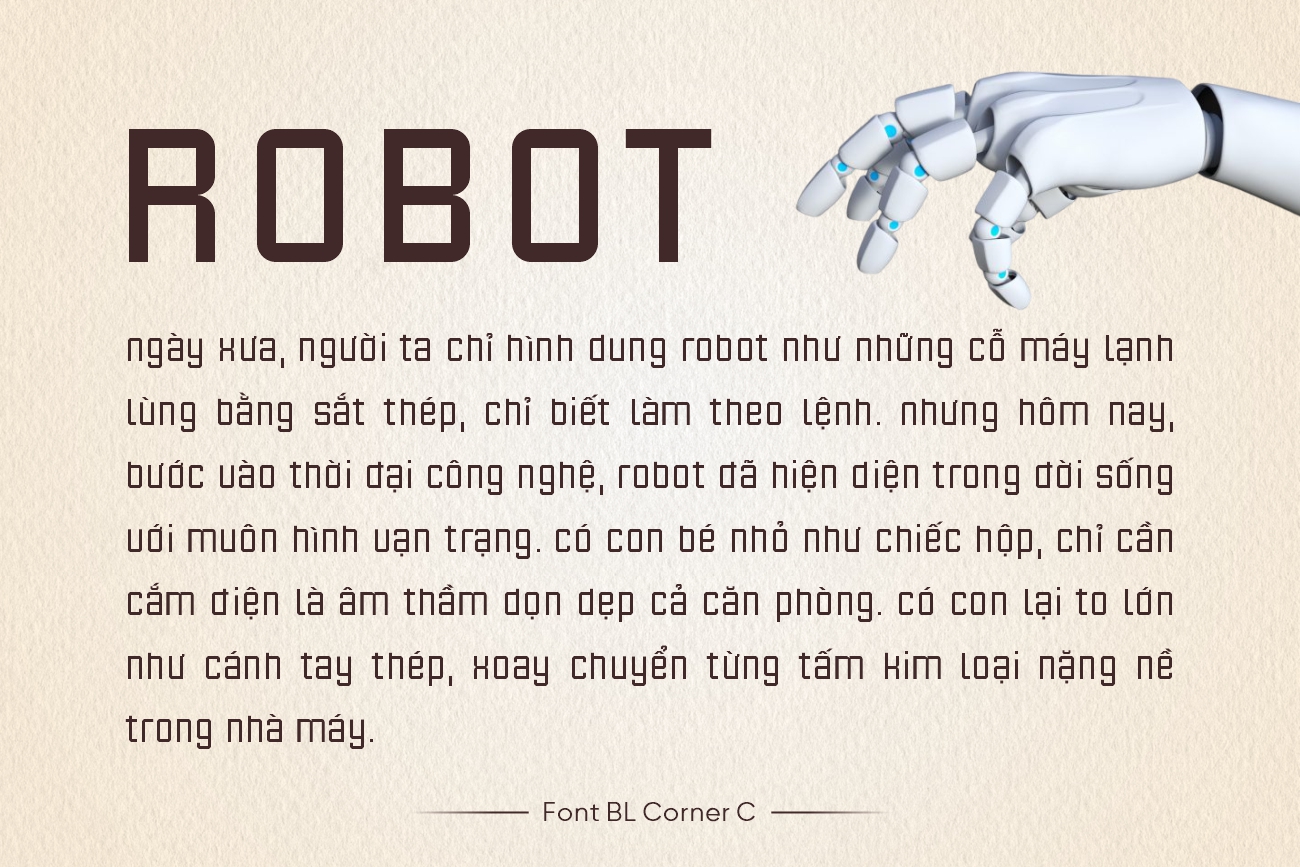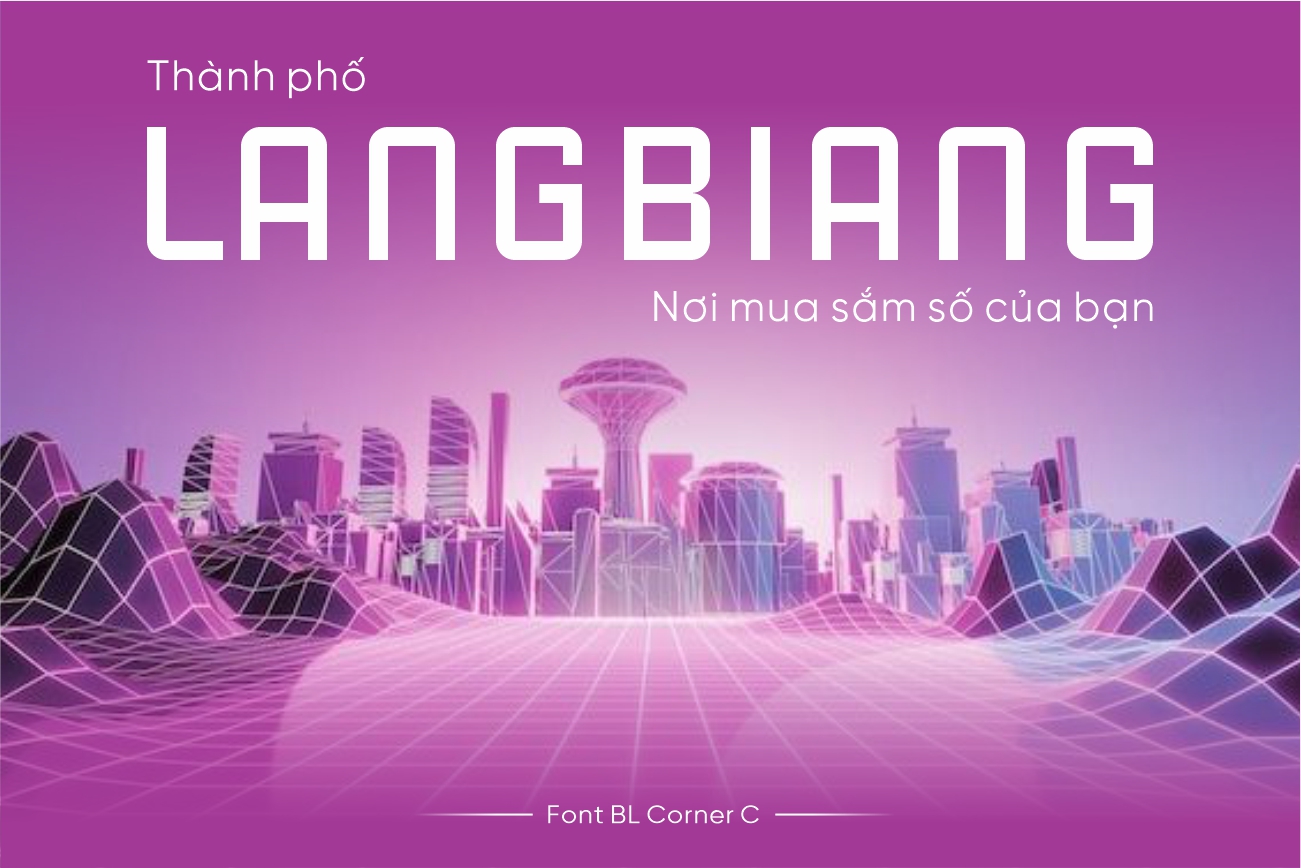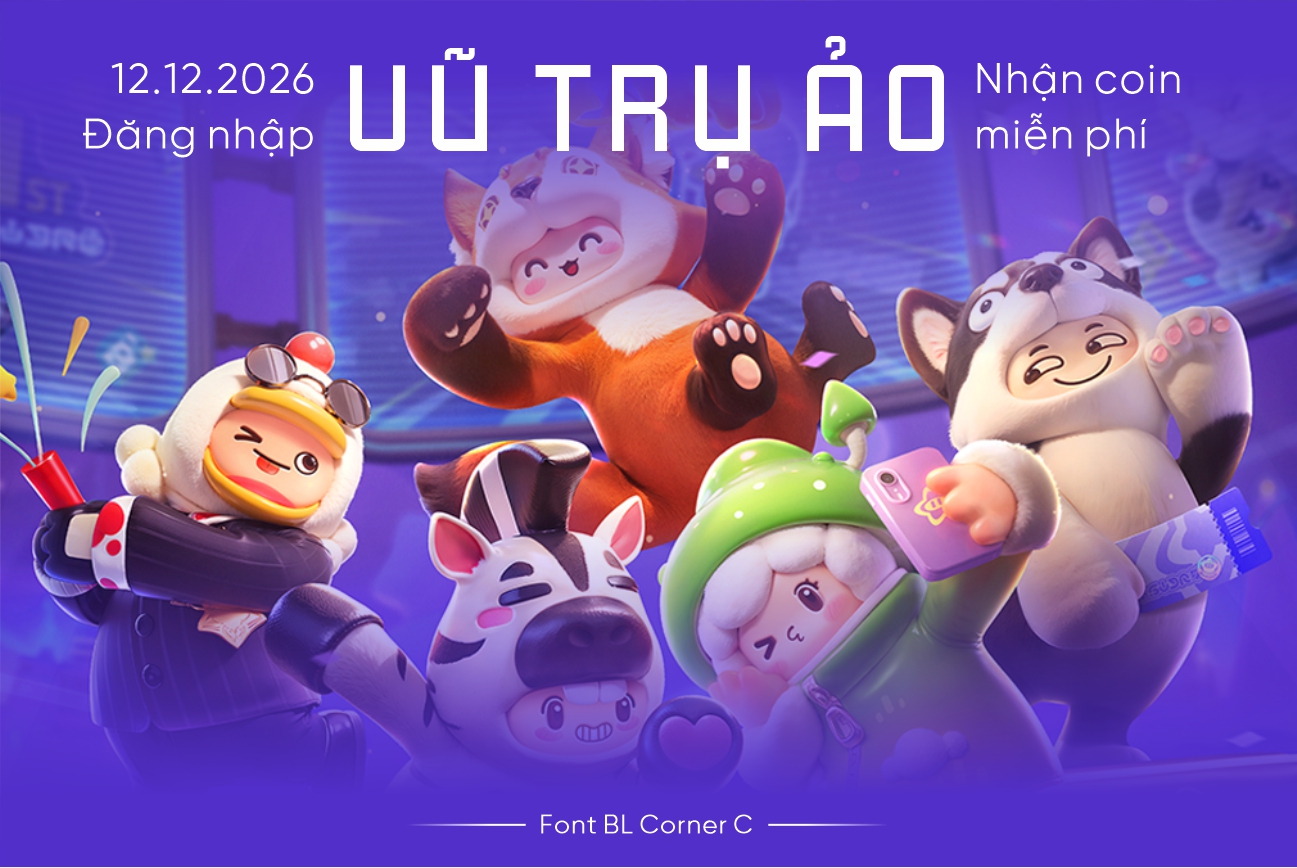
Font chữ công nghệ hiện đại Việt hóa - BL Corner C
Trong thời đại số, thiết kế đồ họa không chỉ dừng lại ở sự sáng tạo mà còn đòi hỏi tính ứng dụng cao và phù hợp với bối cảnh công nghệ phát triển mạnh mẽ. Một trong những lựa chọn nổi bật cho designer chính là BL Corner C – phiên bản font chữ Việt hóa từ Corner C gốc, mang phong cách mạnh mẽ và hiện đại.
BL Corner C gây ấn tượng ngay từ cái nhìn đầu tiên bởi cấu trúc vuông vức, góc cạnh nhưng vẫn có sự bo tròn nhẹ, tạo nên sự cân bằng giữa mạnh mẽ và thân thiện. Kiểu dáng chữ in hoa, đường nét thẳng tắp giúp font mang hơi hướng công nghệ, dễ dàng gợi nhớ đến các thiết kế liên quan đến robot, trí tuệ nhân tạo, công nghiệp 4.0. Đây chính là lý do vì sao BL Corner C được đánh giá cao khi dùng trong các dự án truyền thông về khoa học, kỹ thuật hay công nghệ số.
Không chỉ dừng ở tính thẩm mỹ, BL Corner C còn được team BL Việt hóa đầy đủ dấu tiếng Việt, giúp font trở thành công cụ hoàn hảo cho designer trong nước. Từ tiêu đề poster, banner quảng cáo cho đến thiết kế bao bì, font đều đảm bảo độ rõ ràng, mạnh mẽ và hiện đại.
Ứng dụng của font chữ công nghệ này vô cùng đa dạng: từ thiết kế nhận diện thương hiệu, tiêu đề tạp chí, poster sự kiện, giao diện game cho đến các sản phẩm liên quan đến công nghệ và robot. Với BL Corner C, mỗi thiết kế đều mang đậm tinh thần tương lai, khẳng định cá tính sáng tạo và sự khác biệt.
Nếu bạn đang tìm kiếm một font chữ robot vừa cứng cáp, hiện đại, vừa được Việt hóa để sử dụng thuận tiện trong mọi dự án, thì BL Corner C chính là lựa chọn không thể bỏ qua. Đây là công cụ tuyệt vời giúp designer truyền tải thông điệp về sự đổi mới, công nghệ và bước tiến của thời đại số.